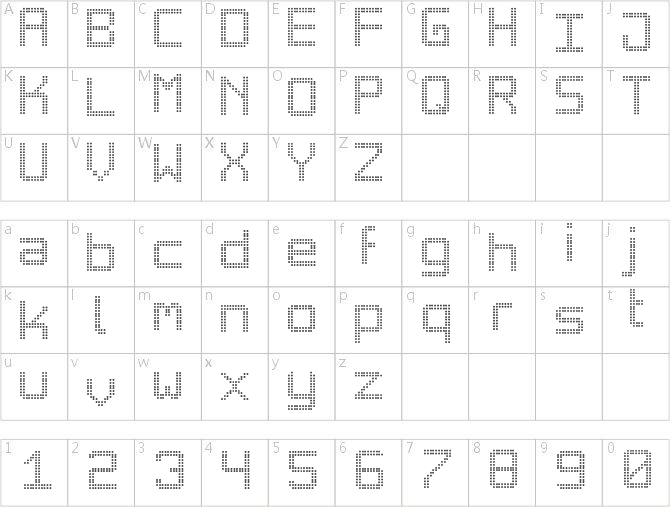
Big-Daddy-LED-TFB 詳情頁
字體名稱: Big-Dad
Big-Daddy-LED-TFB
Big-Daddy-LED-TFB字體字庫是一款讓人賞心悅目、百看不厭的英文字體,適合各類廣告和產品包裝設計應用,字體大小0.11MB,格式為ttf字體,上傳用戶是昊天金誠,作者/版權方為未知